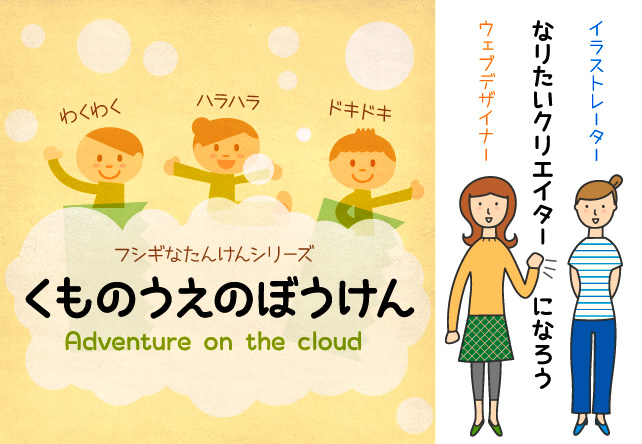
手書き風日本語フォントHAYAO(はやお)フォントとは HAYAO(はやお)は手書き文字を参考にして作成した書体です。手書きの良い部分を活かしつつ統一感のある使いやすいフォント。ワクワクするような明るく元気な雰囲気のデザインにピッタリです。ひらがな、カタカナ、アルファベット、記号のみの書体ですが、一般的な丸ゴシックの漢字と組み合わせて使える、最適な線の太さになっています。  |